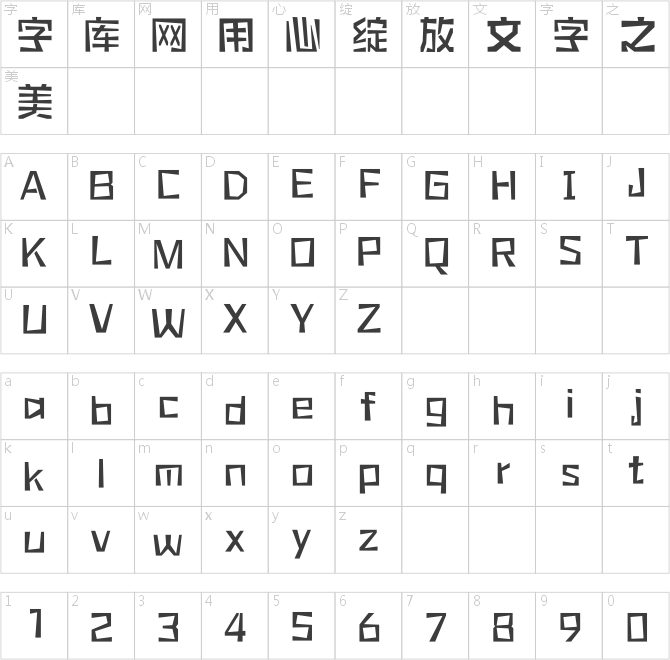
中國(guó)漢字給人的感觀印象是“方塊字”,即在一塊面積大小相等的空間內(nèi),刻畫(huà)出一個(gè)個(gè)獨(dú)立的漢字。比如古代的“活字”雕刻,近代的機(jī)械打字機(jī)“字盤(pán)”。單字之間看似毫無(wú)關(guān)聯(lián),可組合在一起,就能體現(xiàn)出正負(fù)空間的強(qiáng)烈對(duì)比,方陣嚴(yán)整。 該字體筆畫(huà)的安排,沿襲著橡皮章雕刻特有的平直、硬朗,打破傳統(tǒng)的“橫平豎直”,增加字體的動(dòng)感,有古老石碑的拓印之風(fēng),不失時(shí)尚潮流的文藝之美,無(wú)論是橫排或豎排,行列之間整齊有序,給人予方塊拼接,搭積木之美感,可廣泛用于報(bào)紙、雜志、包裝、廣告等印刷品的標(biāo)題、正文。